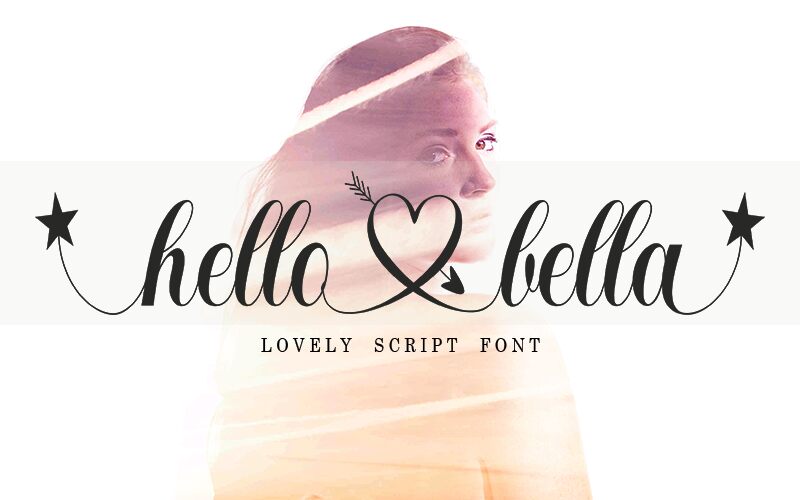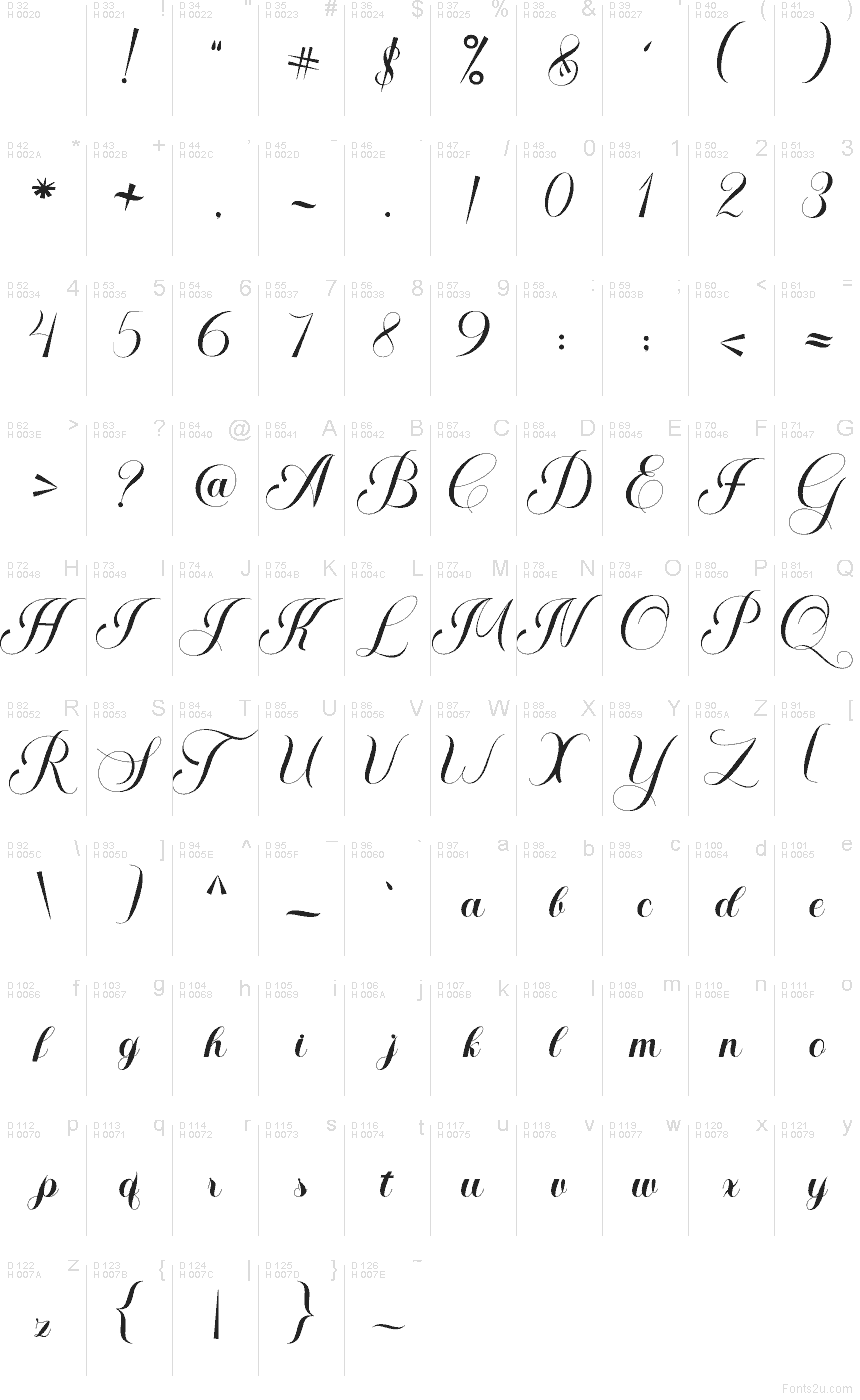
Hello Bella от Bosstype Studio — это бесплатный каллиграфический шрифт с легким романтическим настроением. Буквы отличаются длинными петлями и плавным, связным начертанием; узкие формы и воздушные изгибы делают шрифт более похожим на рукописный, нежели на формальную типографику.
Он отлично подойдет для свадебной полиграфии, брендинга бутиков, упаковки косметики, цитат в соцсетях и журнальных заголовков, где требуется мягкий, плавный почерк. Поскольку линии остаются тонкими, а стиль задают в основном петли, шрифт лучше всего смотрится в коротких названиях, визитках и небольших заголовках, где динамика букв задает тон всему макету.
Включает начальные и конечные декоративные элементы (своши), а также лигатуры для строчных букв.